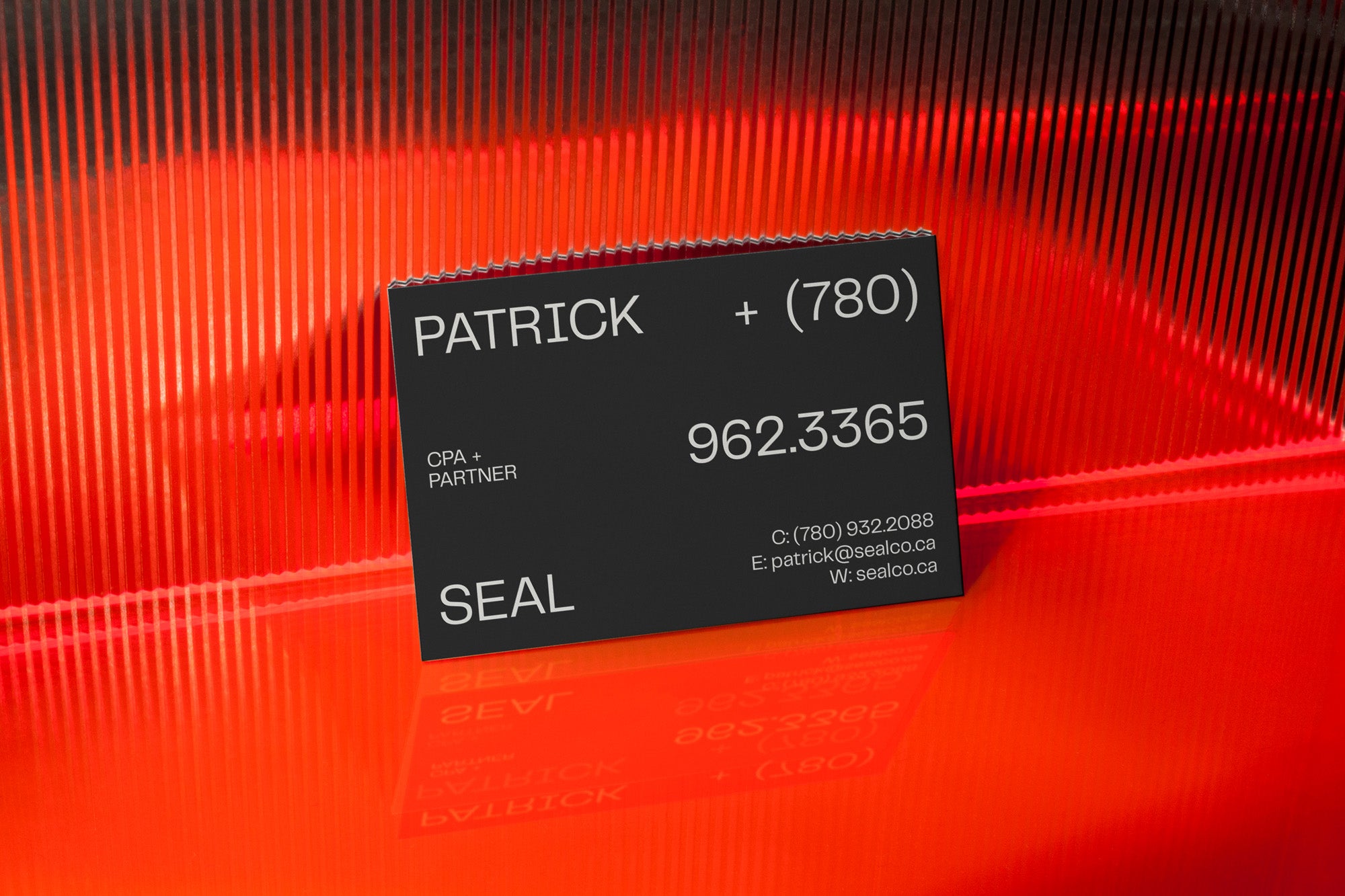
Seal + Co
Le changement de marque Seal+Co, inspiré du Bauhaus, de CUSP met fin aux traditions de la comptabilité d'entreprise
Fondé en 1992, Seal+Co est un cabinet d'expertise comptable basé à Edmonton, au Canada, spécialisé dans les états financiers, les déclarations de revenus, la tenue de livres et l'assistance logicielle. Souhaitant une refonte progressive mais modérée de son image de marque, Seal+Co a fait appel à l'expertise du collectif créatif mondial CUSP, qui a développé une mise à jour contemporaine de son identité existante, tenant compte de ses prédécesseurs.
Ainsi, le système d'identité dégage une impression de confiance, de professionnalisme et de fiabilité, tout en intégrant des éléments plus et ludiques, tels que des formes géométriques de style Bauhaus, pour briser les préjugés corporatifs qui entourent la comptabilité. Conçues pour « véhiculer l'idée de résolution de problèmes de manière abstraite », les formes arrondies se déclinent en différentes versions, allant de contours subtils à des blocs colorés et éclatants.
Sur le plan typographique, l'identité s'articule autour d'une association réfléchie entre Telegraf (Pangram Foundry) et Canela (Commercial Type). Concernant la première, CUSP explique qu'ils souhaitaient « utiliser une police sans empattement à l'allure intemporelle, tout en conservant une certaine personnalité », tandis que Canela, la seconde, offre une juxtaposition affirmée avec ses arêtes vives et ses contrastes élégants. L'identité se marie harmonieusement entre les deux polices, offrant une imprévisibilité stimulante, bien loin du caractère souvent statique des marques financières traditionnelles.
Pour se démarquer davantage de ses concurrents, le studio a introduit l'orange comme couleur d'accent vibrante, en complément de sa palette principale de noir et blanc. « Tous leurs concurrents actuels ont une palette de couleurs très sobre, composée de bleu ou de gris ; l'introduction de l'orange les rend plus agréables et plus accessibles », conclut CUSP.